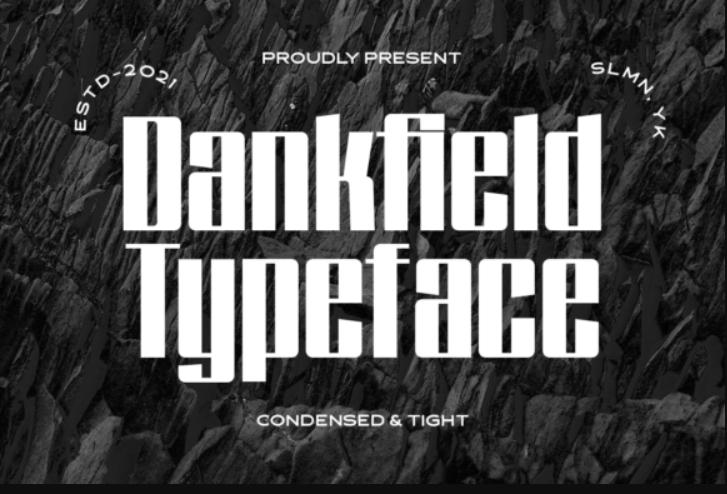
[Creativefabrica] Dankfield Font (letterhend)
Dankfield - это жирный шрифт с толстыми буквами, который выглядит в стиле техно. Он будет отлично смотреться на множестве дизайнов, требующих футуристического, внушительного акцента.